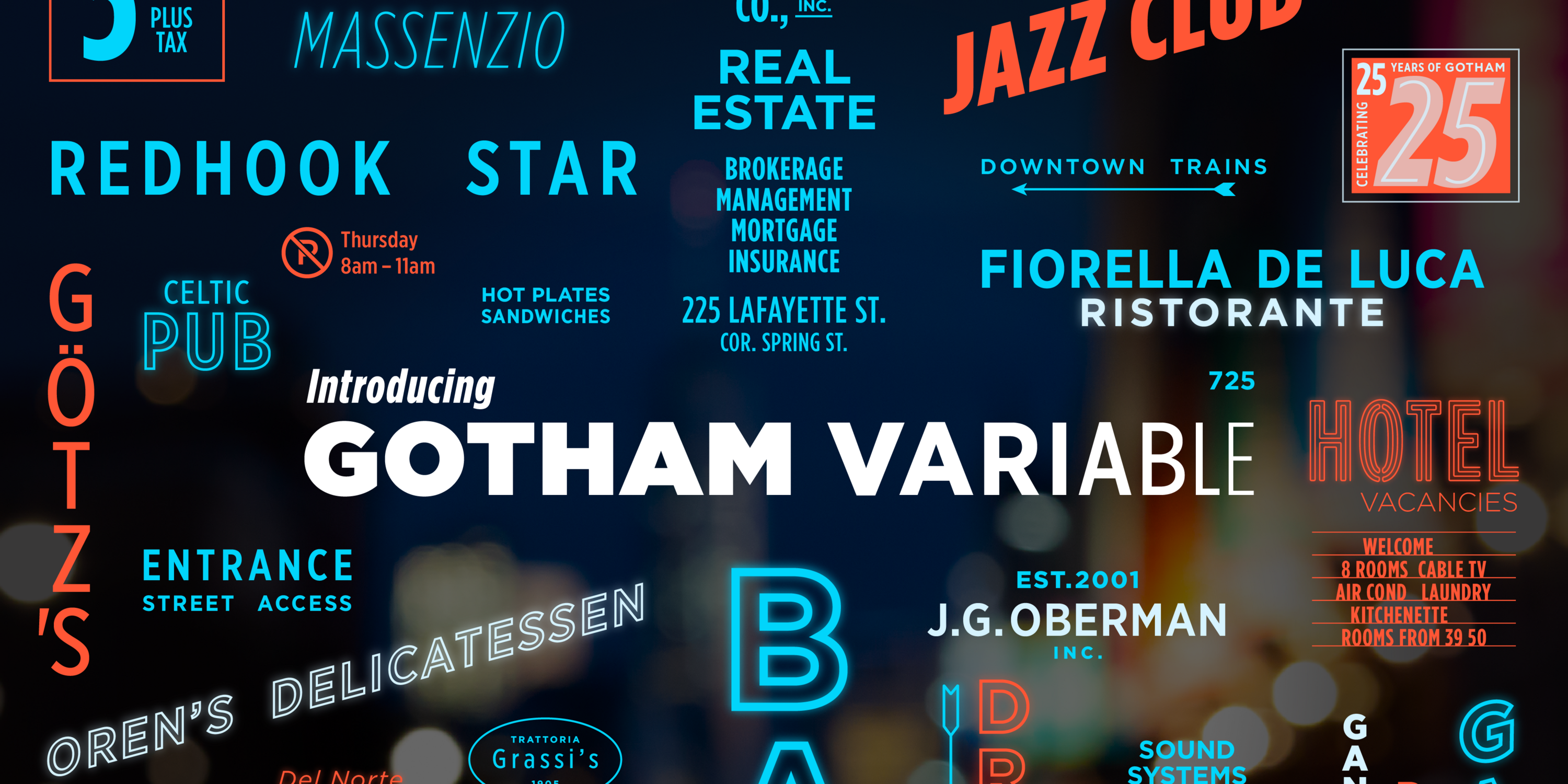
Monotype feiert 25 Jahre Gotham mit der Einführung von Gotham Variable
Mit Gotham Variable entwickelt Monotype die ikonische Schrift zu einem dynamischen Designsystem weiter – mit stufenloser Kontrolle über Gewicht und Breite, erweiterter Sprachunterstützung und einer Ein-Datei-Architektur für moderne Workflows.
Berlin, 12. Mai 2026 – Seit ihrem Debüt vor 25 Jahren auf dem Cover von GQ prägt Gotham die visuelle Kommunikation weltweit – von Markenidentitäten über Werbung bis hin zu Politik und Entertainment. Die Gotham Font Family wurde von Jonathan Hoefler und Tobias Frere-Jones entworfen und von Hoefler & Co. veröffentlicht. Die Schrift hat die Auftritte zahlreicher globaler Marken geprägt, darunter Netflix und Coca-Cola. Auch Institutionen wie der United States Postal Service und Formate wie Saturday Night Live haben auf Gotham gesetzt. Zudem spielte sie eine zentrale Rolle im Präsidentschaftswahlkampf von Barack Obama.
Vom Klassiker zur Variable Font
Vor diesem Hintergrund stellt Monotype mit Gotham®Variabledie nächste Evolutionsstufe vor. Die neue Version entwickelt einen der bekanntesten und meistgenutzten Fonts konsequent weiter und überführt das gestalterische Erbe in die Gegenwart. Gotham Variable eröffnet neue kreative Spielräume durch mehr Flexibilität und Kontrolle.
Mit Gotham Variable können Designer Gewicht und Breite stufenlos anpassen. So lassen sich Tonalität und Ausdruck in Echtzeit steuern – ohne Schriftwechsel und ohne Kompromisse bei der Konsistenz. Mehrere statische Dateien sind in einer einzigen, schlanken Datei gebündelt. Das verbessert die Performance, verkürzt Ladezeiten und vereinfacht die Implementierung über verschiedene Plattformen hinweg. Die Schrift passt sich nahtlos an Screens, Systeme und Nutzungskontexte an – und bewahrt dabei die Klarheit und Souveränität, für die Gotham steht.
„Gotham hat sich über 25 Jahre hinweg ein außergewöhnliches Vertrauen erarbeitet – von politischen Kampagnen über großflächige Außenwerbung bis hin zu einigen der prägendsten Markenauftritte weltweit. Mit Gotham Variable haben wir uns gefragt, welches Potenzial in dieser Schrift noch steckt, ohne ihr starkes gestalterisches Erbe aus den Augen zu verlieren“, sagt Sara Soskolne, heute Executive Creative Director bei Monotype und Lead Designerin von Gotham Variable, ehemals Senior Designerin bei Hoefler & Co. „Viele der neuen Ausprägungen gab es zuvor nicht. Sie so zu gestalten, als hätten sie schon immer dazugehört, war die größte Herausforderung – und zugleich die wichtigste.“
Neben den technischen Neuerungen erweitert Gotham Variable auch die Sprachunterstützung. Neu hinzu kommt Vietnamesisch – eine der letzten großen Lücken im lateinischen Sprachraum. Komplexe diakritische Zeichen, Tonmarkierungen und Akzente werden präzise umgesetzt. So können Marken weltweit klar und authentisch kommunizieren.
„Die Ergänzung einer bestehenden Schriftfamilie um neue Sprachsysteme ist alles andere als trivial“, erklärt Jordan Bell, Senior Type Designer bei Monotype. „Proportionen und Stil mussten exakt stimmen, um die DNA von Gotham zu bewahren. Besonders bei Elementen wie Haken und Hörnern war es entscheidend, die Ausdrucksstärke der Schrift präzise zu treffen.“
Die zentralen Features von Gotham Variable
Zu den wichtigsten Funktionen von Gotham Variable zählen die stufenlose Steuerung von Gewicht und Breite innerhalb einer einzigen Font-Datei sowie eine erweiterte Sprachunterstützung – inklusive Vietnamesisch und optimierter kyrillischer und bulgarischer Zeichensätze. Hinzu kommen neue Zwischenschnitte mit fein abgestuften Gewichtungen und einer zusätzlichen Compact-Breite. Gleichzeitig verbessert Gotham Variable die Performance, verkürzt Ladezeiten und vereinfacht die Implementierung. Die Schrift passt sich zudem nahtlos an digitale und physische Designumgebungen an.
Durch die variable Technologie erweitert Monotype auch den bestehenden Schriftsatz: 54 neue Zwischenschnitte schließen den Designraum der Familie und schaffen zusätzliche gestalterische Spielräume. So entwickelt sich Gotham von einer statischen Schriftfamilie zu einem responsiven System, das die Anforderungen moderner Gestaltung erfüllt – und zugleich seine vertraute gestalterische Stimme bewahrt.